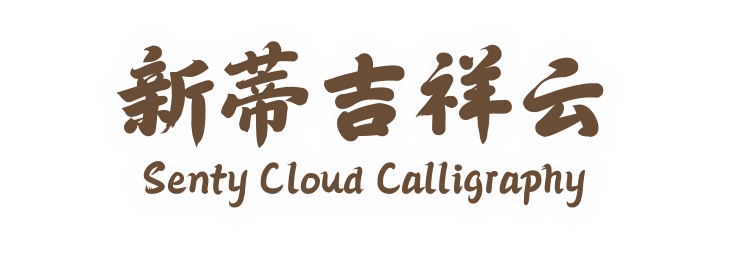
新蒂吉祥云体是全新新蒂字体家族中的一员,它的独特之
处在于其庄严而大气的风格,同时又充满了生动的活力。
这款字体的字形设计注重笔画的厚重感,让每个字的形态
都显得更加饱满和有力,从而赋予文本更强的视觉冲击
力。
与此同时,新蒂吉祥云体也继承了中国传统书写的流畅之
美。在字体的设计中,保留了传统书法的笔画连贯性,使
每个字之间的过渡自然而顺畅。这种流畅性使得文字在排
版时能够更加和谐地融入文本中,不仅增强了字体的可读
性,还赋予了整个文本一种更加动感和生气的氛围。
总的来说,新蒂吉祥云体是一款
既庄严又充满活力的字体,适合
用于各种设计和排版需求,特别
是那些希望突出字体力量和传统
美感的项目。不仅如此,它还能
够避免大字字体常见的僵硬刻板
感,为文本注入了一份独特的生
命力。